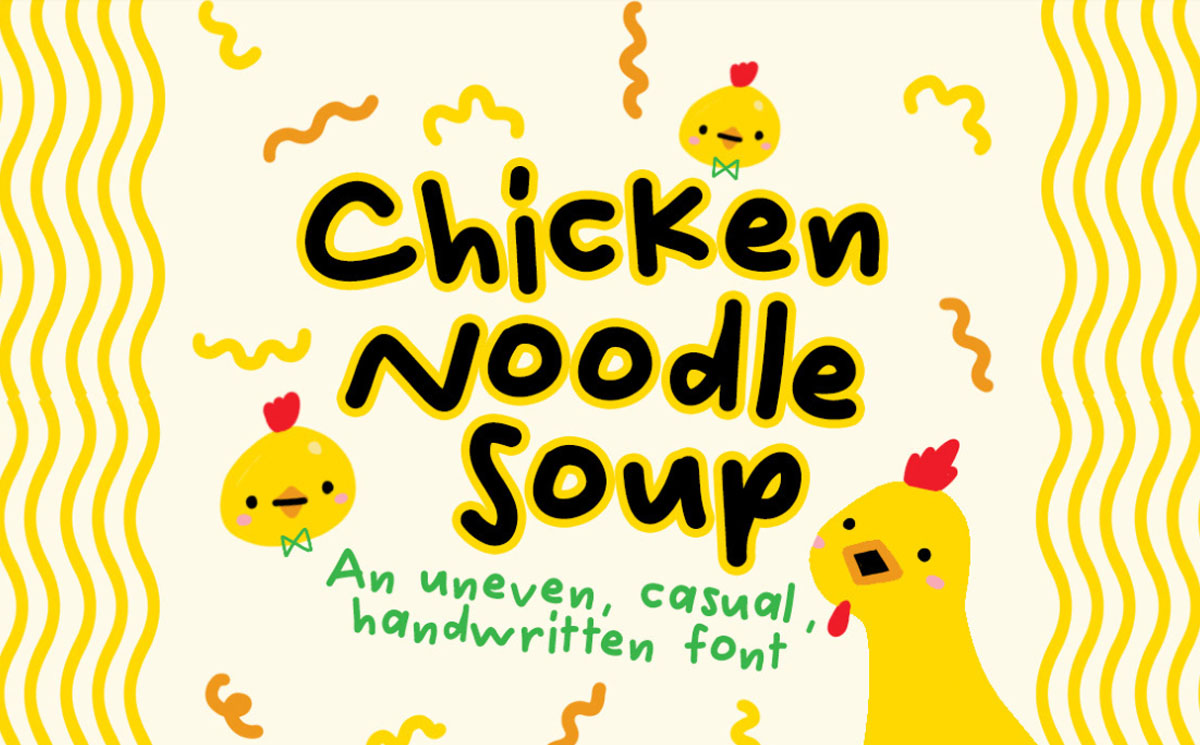
Nếu bạn đang tìm kiếm một phông chữ mang phong cách ngộ nghĩnh, tươi vui để “thổi hồn” vào các dự án thiết kế của mình, thì SVN Chicken Noodle Soup chính là sự lựa chọn không thể hoàn hảo hơn. Được thiết kế theo phong cách hoạt hình đáng yêu kết hợp với đường nét phá cách mượt mà, bộ font này dễ dàng thu hút sự chú ý của người xem ngay từ cái nhìn đầu tiên. Đặc biệt, bản phông chữ đã được Việt hóa hoàn chỉnh và chia sẻ hoàn toàn miễn phí, giúp cộng đồng sáng tạo tại Việt Nam tự do bay bổng với những ý tưởng độc đáo.
Phông chữ SVN Chicken Noodle Soup mang đến một làn gió mới cho xu hướng thiết kế đồ họa hiện đại nhờ tính thẩm mỹ độc đáo và nét cá tính năng động. Dưới đây là các tính năng và ưu điểm nổi bật giúp bộ font này trở thành công cụ không thể thiếu của các nhà thiết kế:
Phong cách thiết kế hoạt hình ngộ nghĩnh, đập tan sự gò bó
SVN Chicken Noodle Soup gây ấn tượng mạnh nhờ vào các đường nét bo tròn tự nhiên, kích thước chữ được sắp xếp không đồng đều một cách cố ý tạo nên sự nhịp nhàng, dí dỏm. Không giống như các phông chữ truyền thống vốn mang tính trang trọng và gò bó, font hoạt hình này đem lại cảm giác thân thiện, gần gũi và đầy năng lượng tích cực. Sự ngẫu hứng trong cấu trúc nét thanh nét đậm giúp từng dòng chữ như đang “kể chuyện”, cực kỳ thích hợp cho các ấn phẩm trang trí, quà tặng hay nội dung dành cho giới trẻ và trẻ em.
Hỗ trợ trọn bộ tiếng Việt chuẩn chỉnh theo chuẩn SVN
Trở ngại lớn nhất của nhiều nhà thiết kế tại Việt Nam khi sử dụng các font chữ nước ngoài là lỗi dấu thanh (sắc, huyền, hỏi, ngã, nặng) bị lệch vị trí hoặc không hiển thị đúng định dạng. Nhờ sự chỉnh chu của nhóm Việt hóa SVN, SVN Chicken Noodle Soup được tích hợp trọn bộ ký tự tiếng Việt chuẩn mã Unicode. Các dấu thanh được đặt vị trí vô cùng cân đối, hài hòa với tổng thể nét chữ. Các ký tự đặc biệt như ơ, ư, ê, đ… đều được tinh chỉnh tỉ mỉ để giữ nguyên vẻ đẹp “cute” ban đầu mà vẫn đảm bảo tính chính xác về mặt ngữ pháp.
Tính ứng dụng linh hoạt cho nhiều dự án thiết kế sáng tạo
Dù mang phong cách hoạt hình đậm nét, SVN Chicken Noodle Soup lại sở hữu khả năng thích ứng tuyệt vời trong nhiều lĩnh vực truyền thông và tiếp thị. Bộ font này thường xuyên được sử dụng trong các ấn phẩm đa dạng như:
- Bìa sách, truyện tranh trẻ em: Tạo cảm giác hào hứng, kích thích trí tưởng tượng và sự tò mò của độc giả nhí.
- Bao bì thực phẩm, đồ uống: Thích hợp cho các thương hiệu trà sữa, đồ ăn vặt, bánh kẹo hoặc các nhà hàng mang phong cách vui tươi.
- Thumbnail YouTube & Hình ảnh Social Media: Tăng tỷ lệ nhấp (CTR) nhờ các tiêu đề nổi bật, bắt mắt và mang lại nét thân thiện trên Fanpage, TikTok hay Instagram.
- Thời trang và Quà tặng: Thiết kế hình in lên áo thun, ly cốc, nón, sticker, thiệp sinh nhật hoặc thiệp mừng sự kiện.
Tối ưu hiển thị sắc nét trên cả bản in lẫn nền tảng kỹ thuật số
Các đường nét đường cong của SVN Chicken Noodle Soup được vẽ bằng hệ thống vector vô cùng sạch vẽ và chính xác. Nhờ đó, khi bạn phóng to chữ để in ấn các tấm banner, poster khổ lớn hay bảng hiệu cửa hàng, phông chữ vẫn giữ nguyên độ nét mượt mà, không bị răng cưa hay vỡ nét. Đồng thời, trên màn hình các thiết bị điện tử, nét bo tròn giúp font chữ hiển thị dễ chịu, không gây mỏi mắt cho người xem ngay cả ở định dạng hiển thị kích thước nhỏ.
Ý Tưởng Phối Phông Và Hiệu Ứng Đồ Họa Đẹp Nhất Với SVN Chicken Noodle Soup
Để biến những dòng chữ SVN Chicken Noodle Soup trở nên ấn tượng và sống động hơn trong bản vẽ, bạn có thể kết hợp áp dụng một số thủ thuật thiết kế đơn giản sau:
- Thêm viền (Stroke) và Bóng đổ (Drop Shadow): Thêm một đường viền màu trắng hoặc tương phản dày xung quanh chữ, kết hợp cùng hiệu ứng bóng đổ sẽ giúp tiêu đề nổi bật hoàn toàn trên các bức ảnh nền nhiều chi tiết.
- Tạo hiệu ứng 3D hoặc Bánh Mì (Puffy 3D): Phong cách nét chữ tròn của font rất phù hợp để làm hiệu ứng chữ nổi 3D, giả chất liệu đất nặn hoặc kẹo dẻo vô cùng bắt mắt.
- Phối màu Gradient rực rỡ: Sử dụng các dải màu chuyển pastel hoặc màu neon rực rỡ như vàng – cam, hồng – xanh để nhân đôi sự thu hút cho mắt người nhìn.
- Phối hợp font chữ (Font Pairing): Hãy dùng SVN Chicken Noodle Soup cho tiêu đề chính (Headline) và kết hợp với một font chữ không chân (Sans-serif) đơn giản cho phần nội dung chi tiết để tạo nên bố cục phân cấp thông tin mạch lạc.
▪️ Nhà thiết kế: Quirky Queen Media
▪️ Nhà phát hành: Quirky Queen Media
▪️ Việt hóa: STYLEno.1 Fonts